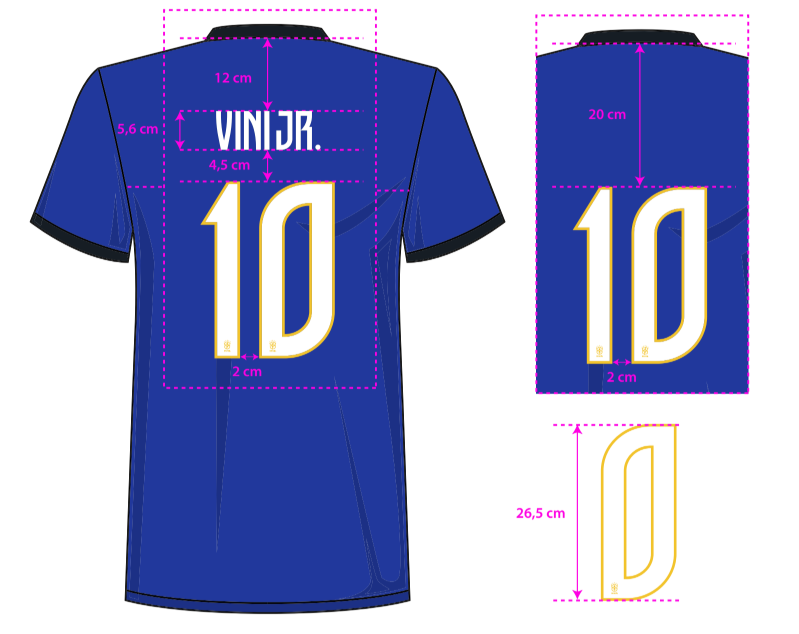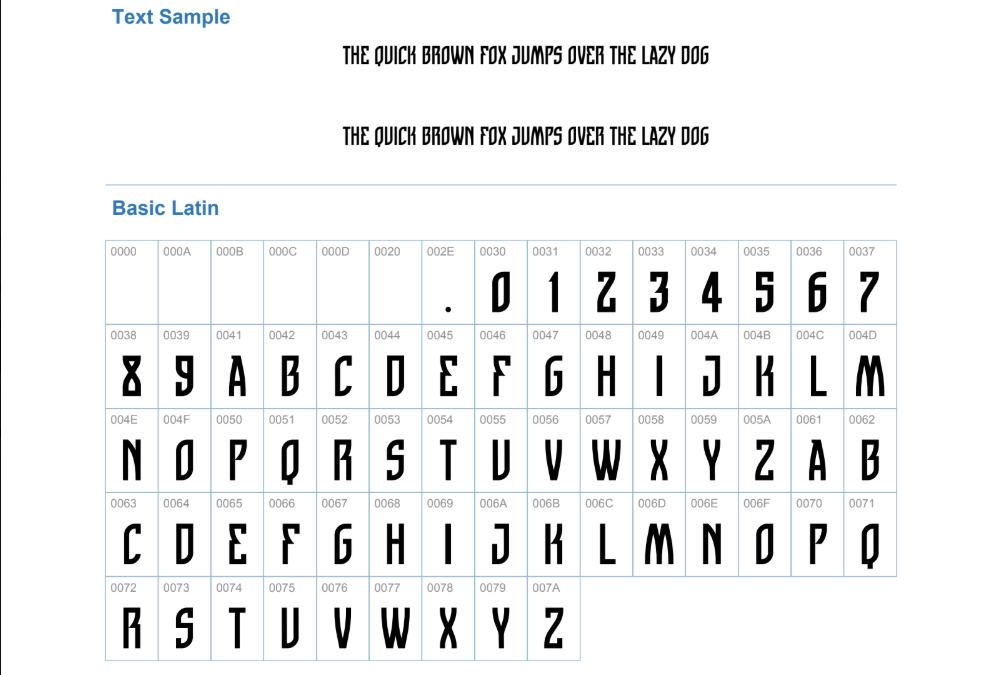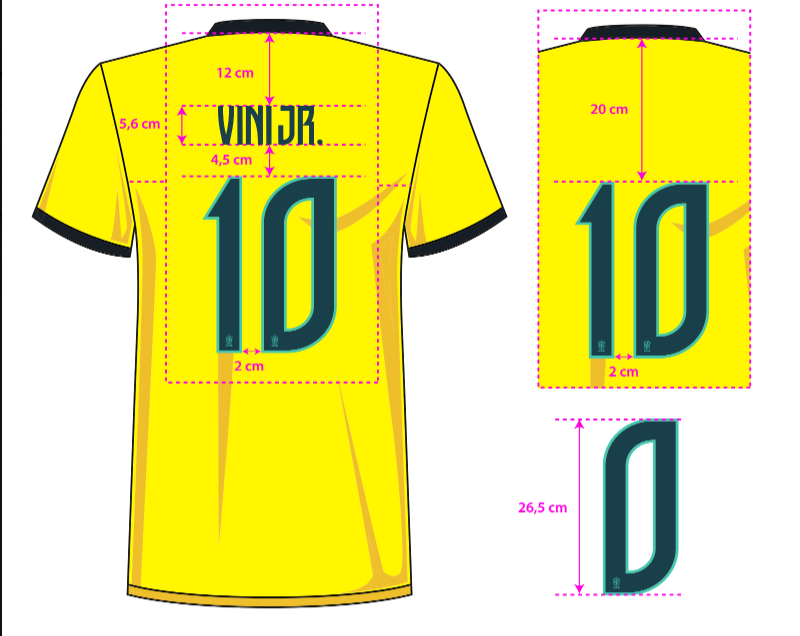
A Copa do Mundo é sempre um marco para a Seleção Brasileira, e a identidade visual dos uniformes reflete a paixão e a tradição do futebol pentacampeão. Em continuidade à icônica parceria com a fornecedora esportiva (Nike), os mantos canarinhos trazem não apenas inovação tecnológica nos tecidos, mas também uma tipografia exclusiva que complementa o design clássico da camisa amarela e do uniforme reserva azul.
Para designers gráficos, editores de jogos (como eFootball e EA Sports FC) e criadores de conteúdo esportivo, utilizar a fonte correta é o detalhe que separa um trabalho amador de um profissional. A numeração e os nomes nas costas das camisas possuem um papel crucial na estética do uniforme, garantindo legibilidade e estilo dentro e fora dos gramados.
Neste post, disponibilizamos a fonte Seleção Brasileira Copa, uma recriação de alta fidelidade inspirada na tipografia utilizada por nossos craques nas competições oficiais.
Estilo visual da tipografia
A tipografia desenvolvida para a Seleção Brasileira nas Copas do Mundo segue uma linguagem visual que mistura a modernidade atlética com a identidade do país.
- Estética: A fonte apresenta um design dinâmico e marcante, transmitindo a velocidade e a habilidade do futebol brasileiro. Os caracteres possuem recortes e ângulos pensados para facilitar a visualização à distância e nas transmissões globais de TV.
- Aplicação:
- Uniforme 1 (Home): Geralmente aplicada na cor verde (ou tons vibrantes) sobre a clássica camisa amarela, garantindo contraste absoluto.
- Uniforme 2 (Away): Aplicada em branco, amarelo ou verde claro sobre a base azul escuro da camisa.
- Personalidade: Ao contrário de fontes esportivas genéricas, esta tipografia possui traços sutis que se alinham à grandiosidade da equipe, mantendo a essência inconfundível do Brasil em campo.